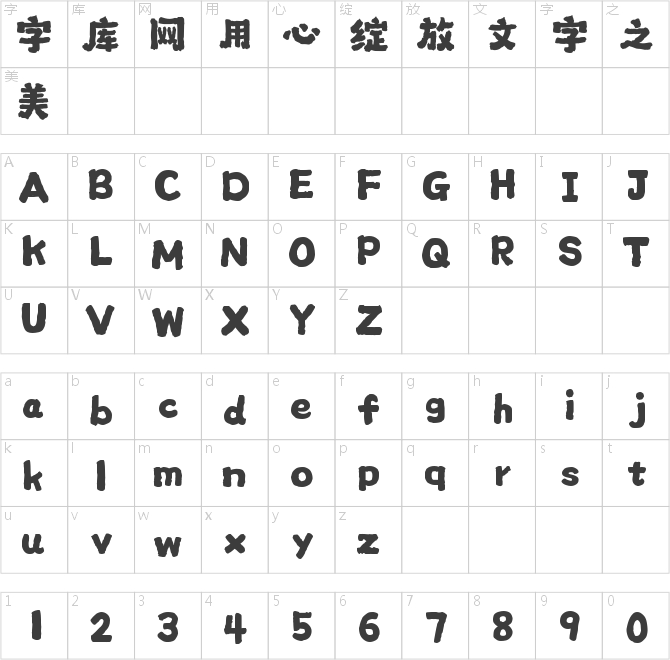
字体名称: 山海朴墨手书
山海朴墨手书
山海朴墨手书,是一款毛笔字体,包含简体汉字6763个。这款字体书写笔锋厚重,同时用笔轻松随性,整体给人一种放松柔美的视觉效果。笔画的飞白效果使字体的气息更加流畅,笔画间的关系密不可分,同时也增加了字体的自由洒脱之感。
山海朴墨手书字体字库是一款让人赏心悦目、百看不厌的中文字体,适合各类广告和产品包装设计应用,字体大小7.72MB,格式为ttf字体,上传用户是山海字库,作者/版权方为山海字库